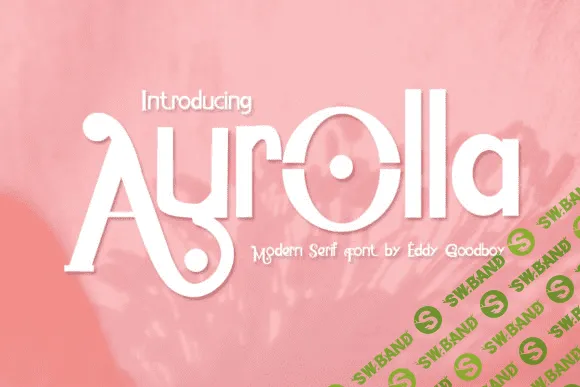
Название: Aurolla Font
Ауролла - это прохладный и четкий шрифт.
Этот шрифт, созданный специально для того, чтобы ваше творение выглядело из этого мира, имеет потенциал для того, чтобы продвинуть ваши творческие идеи намного дальше.